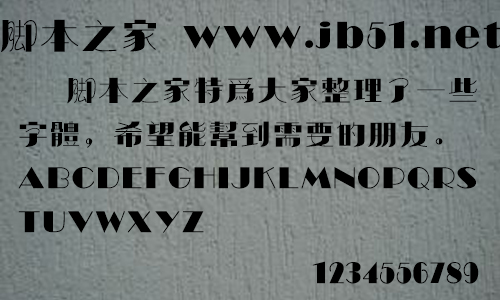
漢儀海紋體繁字體是漢儀字體庫(kù)中的一種字體,漢儀海紋體簡(jiǎn)字體將宋體字橫細(xì)豎粗的特點(diǎn)夸張至極致。纖細(xì)相挽粗重襯托柔韌,粗重搭配纖細(xì)更顯雄壯。強(qiáng)烈的對(duì)比盡顯體勢(shì)勁媚、骨力遒健的藝術(shù)風(fēng)格。適合應(yīng)用于藝術(shù)設(shè)計(jì)、平面宣傳設(shè)計(jì)、網(wǎng)頁(yè)設(shè)計(jì),海報(bào)設(shè)計(jì)等領(lǐng)域,需要的朋友可以前來(lái)本站下載。